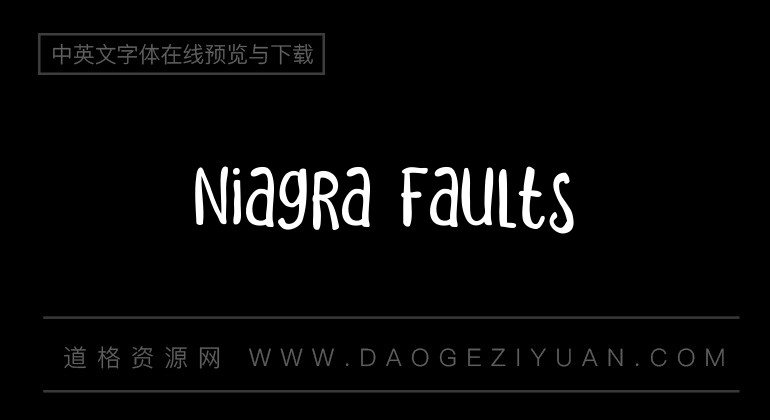
Niagra Faults
Niagara Faults字体是一款简洁、时尚、现代的英文字体,由美国设计师Kris Sowersby于2018年设计。Niagara Faults字体采用了现代的设计理念,结合了细节丰富的字型,在英文字体中脱颖而出。它的字形清晰、比例协调,在文本内容中能够给人以清新、舒服的感觉。Niagara Faults字体可以用于各种场景的文字排版,包括广告、报纸、网站、书籍、报告等。
Niagra Faults是一款非常不错的手写艺术字体,具有很好的视觉感,适合于文化类的宣传设计、商业类品牌的广告和产品包装设计以及个性化文字排版等较多场景。